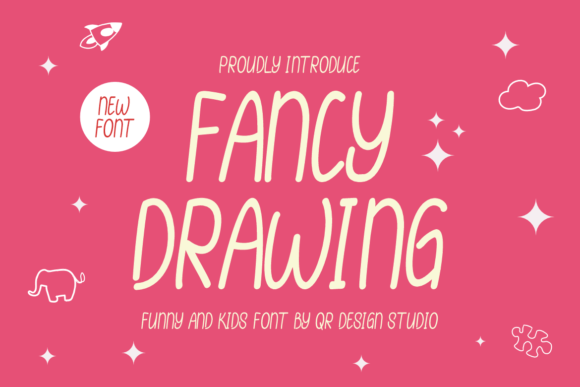
Fancy Drawing
Si vous recherchez des ressources de haute qualité comme Fancy Drawing, ce pack premium est un choix fantastique pour vos projets créatifs.
Que vous créiez des produits POD (impression à la demande), des invitations de mariage ou des visuels pour les réseaux sociaux, Fancy Drawing est un choix idéal.